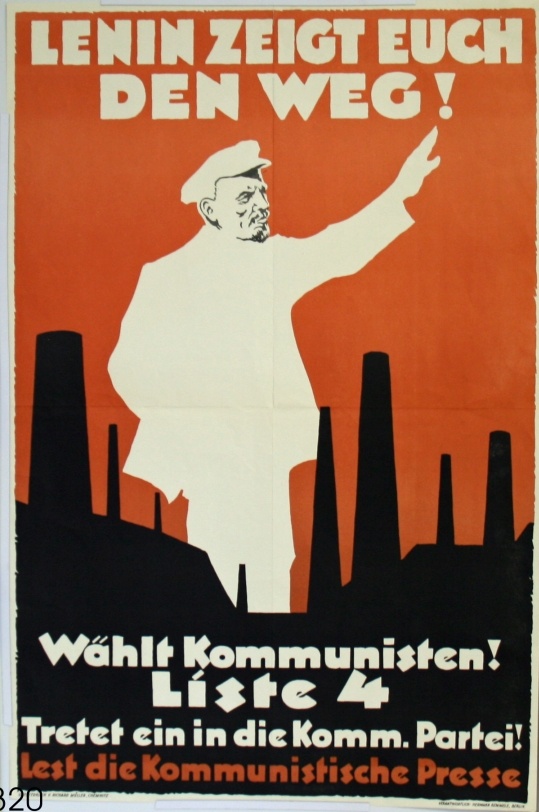
Ich suche eine alte Display-/Plakatschrift (Lenin zeigt euch den Weg)
Für die Gestaltung eines Plakats suche ich u.a. diese – oder eine sehr ähnliche – Schrift. Die hab ich schon auf diversen Schiffsplakaten oder alten deutschen sozialistischen Propagandapostern gesehen (deshalb »Lenin«). Aber immer nur handgemalt, glaube ich, deshalb suche ich nach einer digitalen Entsprechung.